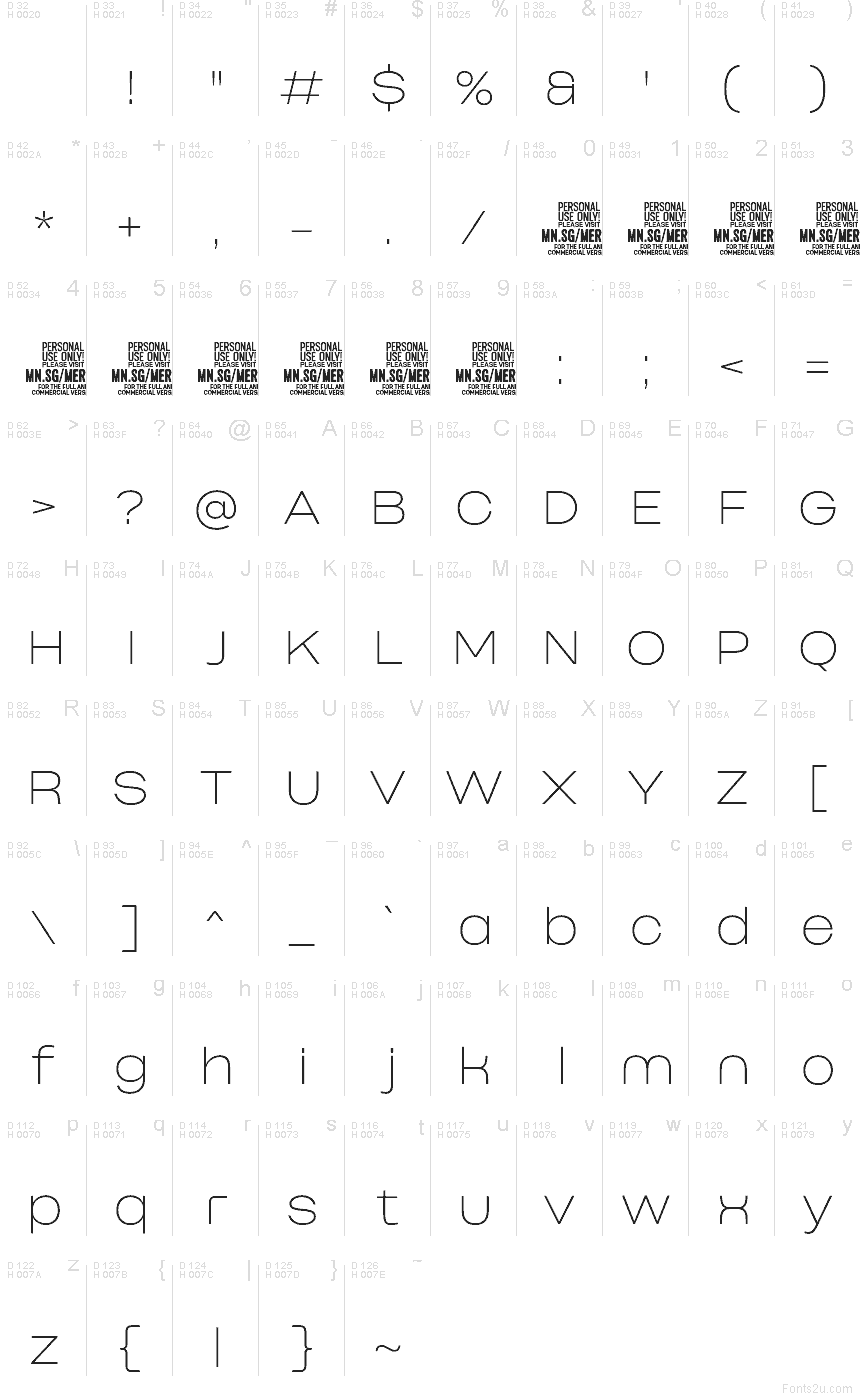
Merica Futurist PERSONAL USE Thin
Merica Futurist von Mans Greback AB ist eine kostenlose, filigrane geometrische serifenlose Schrift mit einem coolen Retro-Futurismus-Flair. Die Buchstaben wirken luftig und sorgfältig reduziert; sie kombinieren fast monolineare Striche mit offenen Kurven und kantigen Abschlüssen, die dem Alphabet eine schnittige, statt weiche Ausstrahlung verleihen.
Die Schrift eignet sich perfekt für Tech-Branding, Sci-Fi-Poster, Fashion-Lookbooks, Albumcover und Titelkarten, bei denen eine schlanke Silhouette den Ton angeben soll. Als kostenlose Schriftart funktioniert sie auch hervorragend für kurze Schlagzeilen, Wortmarken und Grafikdesign im Interface-Stil, besonders wenn ein moderner Look mit einem leicht spekulativen, futuristischen Touch gewünscht ist.